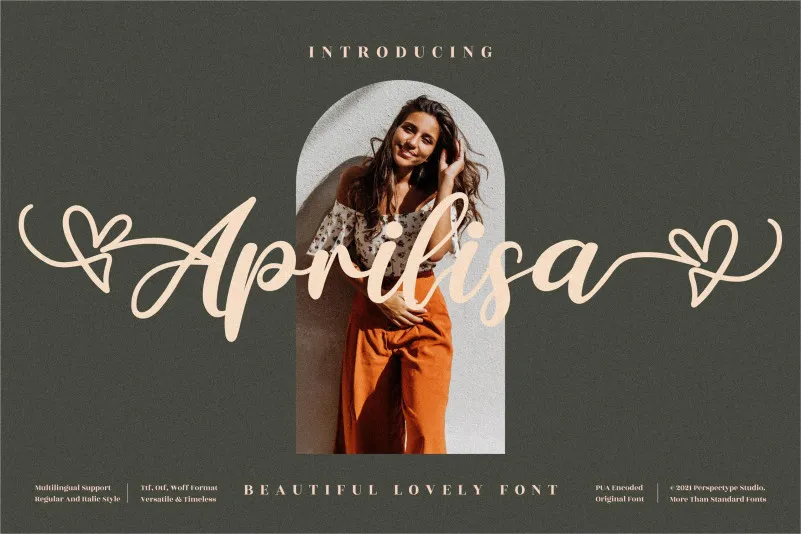
Esta é uma fonte de escrita manual única e elegante. Ela se destaca por sua beleza, especialmente quando usada para personalizar designs que valorizam a singularidade, como cartões de convidados, cartas de agradecimento, convites de casamento, cartazes de boas-vindas, logotipos e muito mais. Esta font é PUA encodificada o que significa que você pode acessar todos os gílios e swashes sem qualquer dificuldade. Perfumada por sua estética única, a Aprilisa pode transformar um design em algo ainda mais especial. Seja para uma festa de casamento memorável ou para criar um logotipo icônico, essa font oferece personalidade e elegância que vão deixar seu trabalho em designs exclusivos com um toque único.